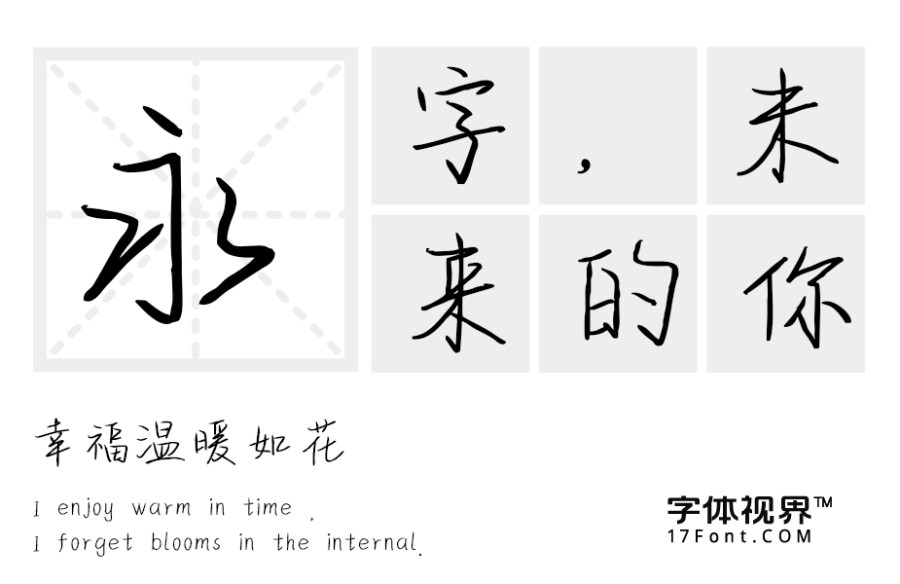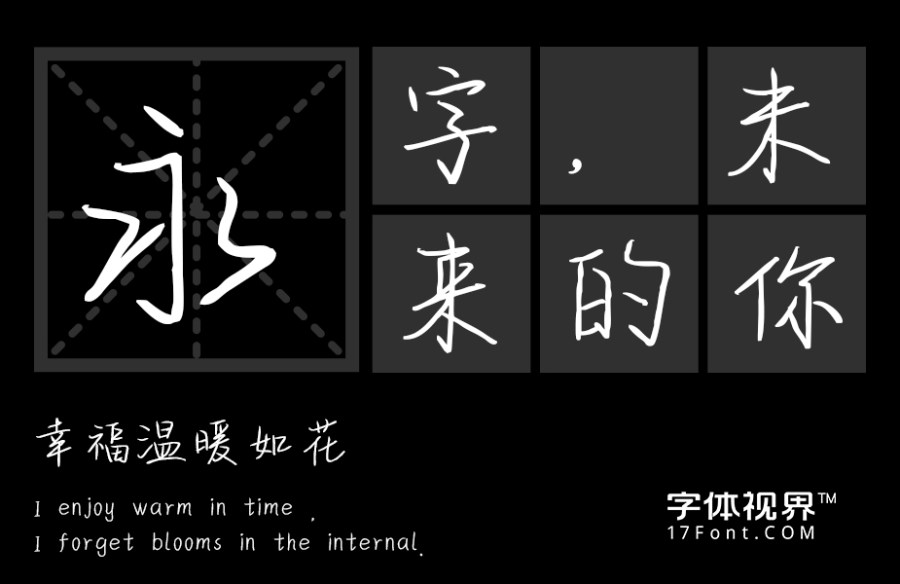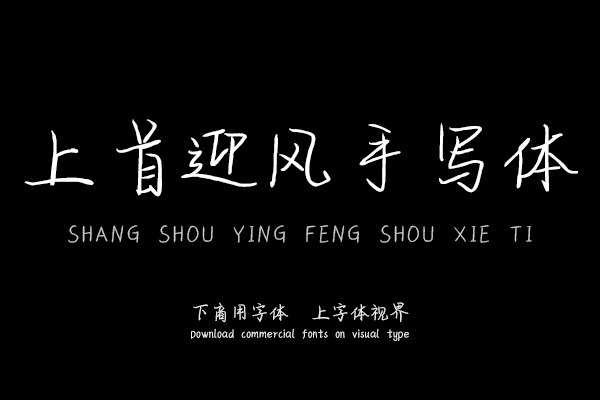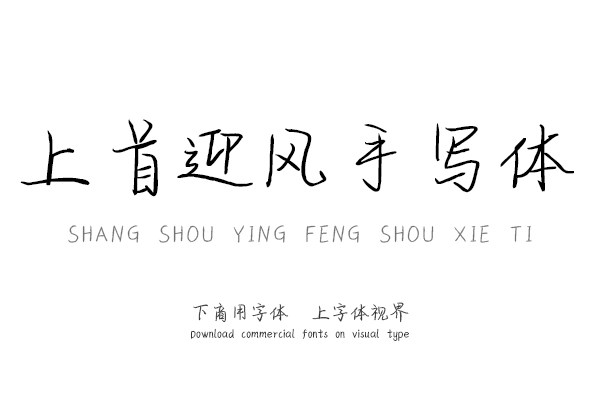
上首迎风手写体,简体中文约6763字,字体笔画潇洒,从容凸显个性,给人极度轻松舒适感,适用于搭配标志、广告标语、商业广告等高端属性。购买须知:“下载服务费”与“字体VIP”所获得字体 仅用于个人非商用, 商用请联系付费授权。本字体为电脑用字,手机没有root权限不支持直接手机换字(手机如何root,请自行百度搜索教程)。购买前请先 了解清楚后再付款 ,字体为虚拟产品无法回收 一旦购买不支持退款。